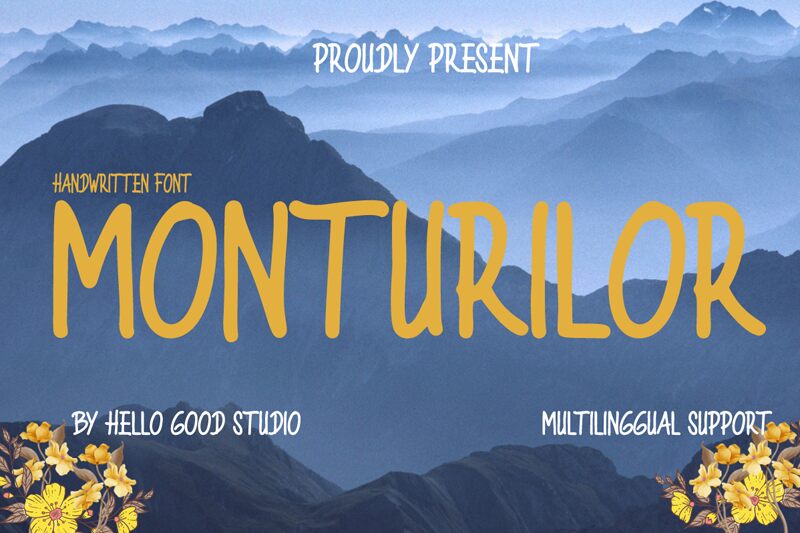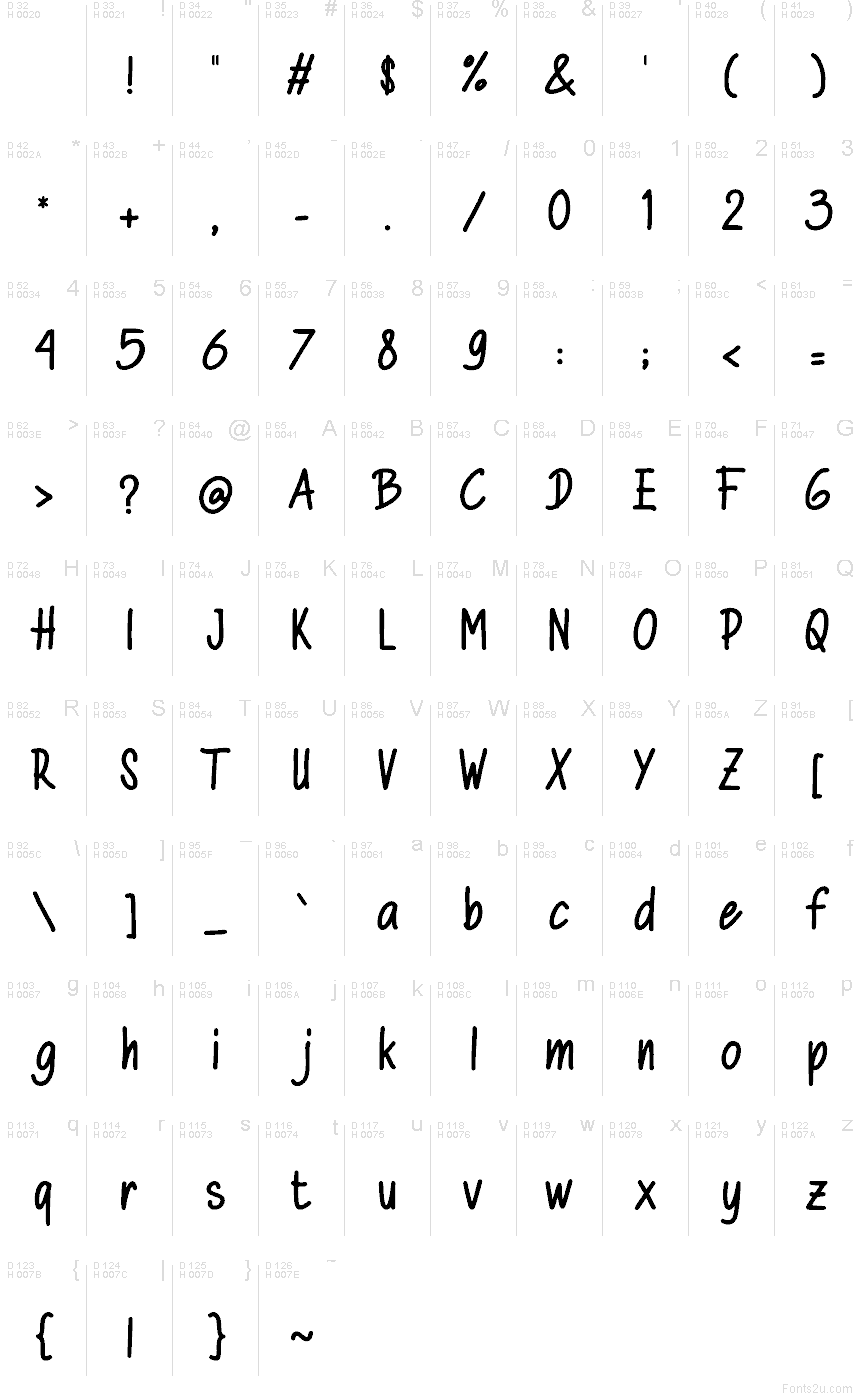
خط Monturilor هو خط مجاني مكتوب بخط اليد يتميز بضربات عالية وضيقة ونهايات مستديرة ناعمة تمنح الحروف إيقاعاً عفوياً يشبه الكتابة بأقلام التحديد. تظل الأشكال بسيطة ومستقيمة، مع لمسة يدوية ثابتة وغير منتظمة قليلاً، مما يجعل المجموعة تبدو مريحة دون أن تبدو فوضوية.
يُعد Monturilor مثالياً للشعارات، ولافتات المقاهي، وتصاميم الاقتباسات، والتغليف، وعناوين الملصقات، ورؤوس صفحات التواصل الاجتماعي، لأن الأشكال تعطي طابعاً شخصياً ومباشراً. هذا الخط المجاني يضفي صبغة يدوية على المشاريع التي تحتاج إلى لمسة سريعة تشبه الاسكتش، خاصة عندما ترغب في جعل الأسماء أو العبارات القصيرة أو الملصقات تبدو غير رسمية وودودة.